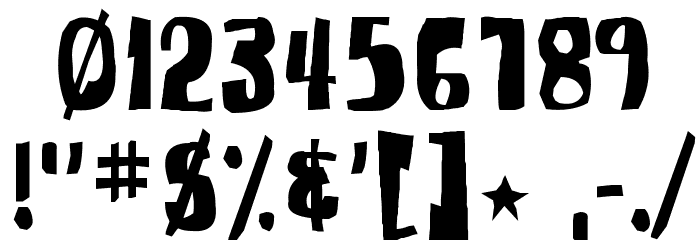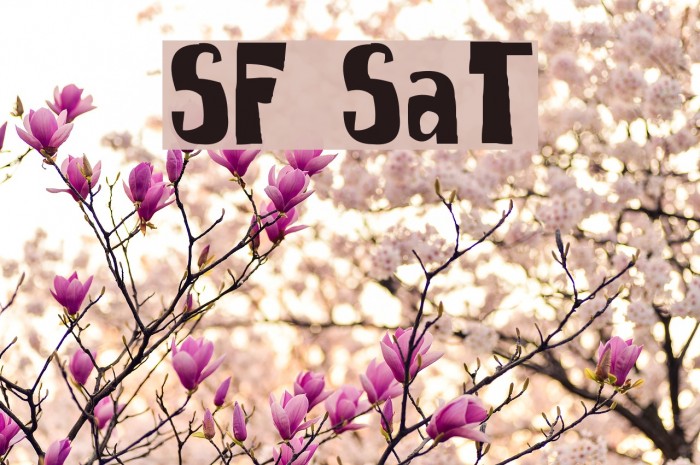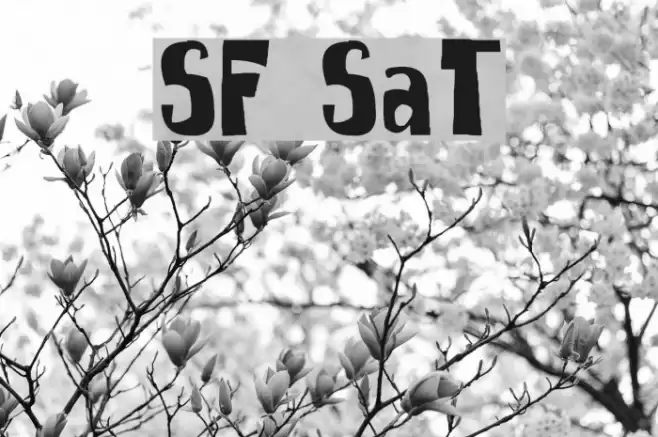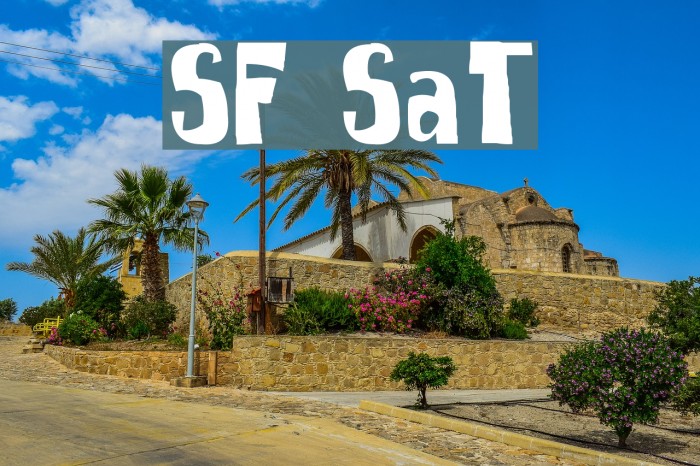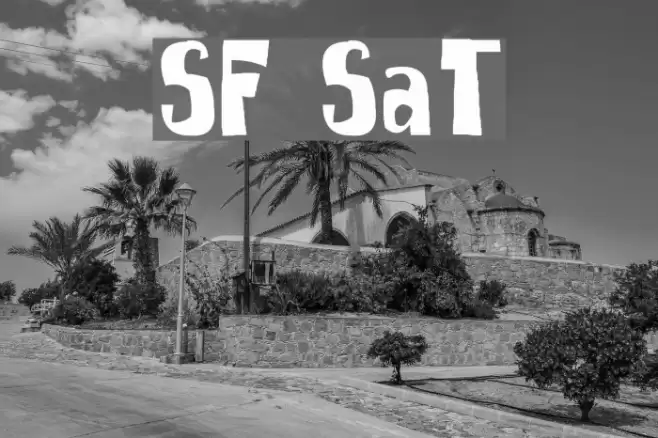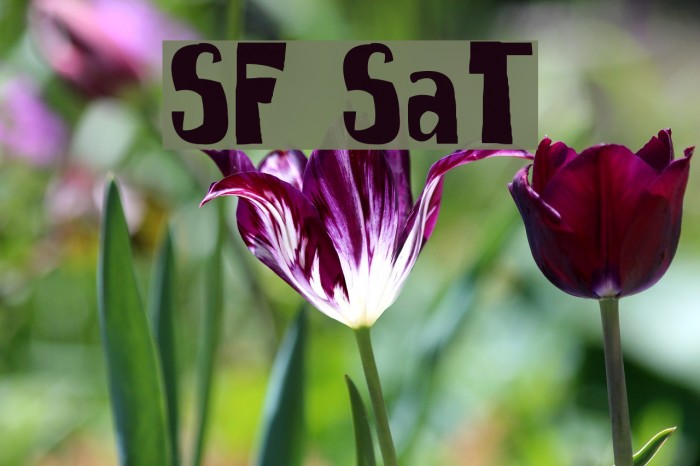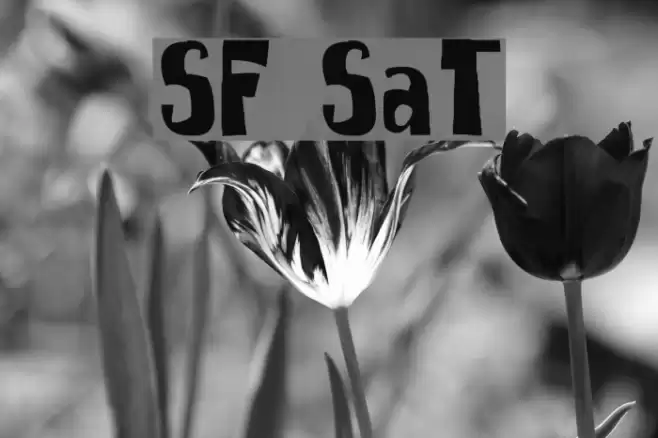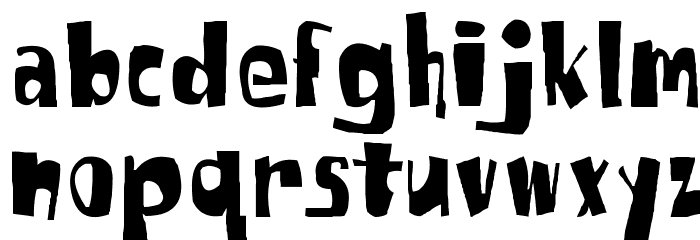
SpongeFont SquareType Font
| Estilo geral | Playful, Quirky, Hand-drawn |
| Caso de uso | Headlines, Posters, Creative Branding |
| Projetos propostos | Ideal for children's books, comic strips, playful branding, and creative posters. |